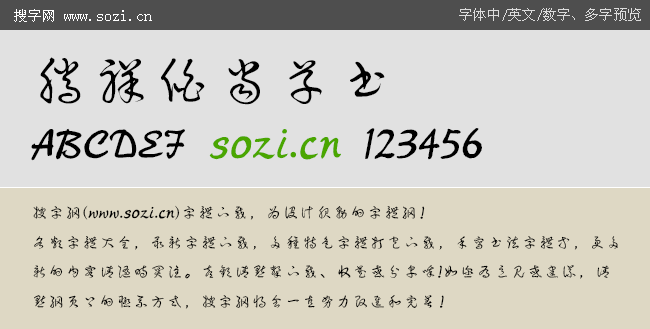
騰祥伯當(dāng)草書
搜字網(wǎng)提供一款騰祥伯當(dāng)草書中文書法字體下載,騰祥伯當(dāng)草書字體是一款非常個(gè)性化的草書字體,字形具有瘦勁、靈動(dòng)的特點(diǎn),英文字簡單又美觀,中文字具有龍飛鳳舞的美感。可以應(yīng)用于美術(shù)設(shè)計(jì)、宣傳海報(bào)、書籍設(shè)計(jì)等領(lǐng)域。